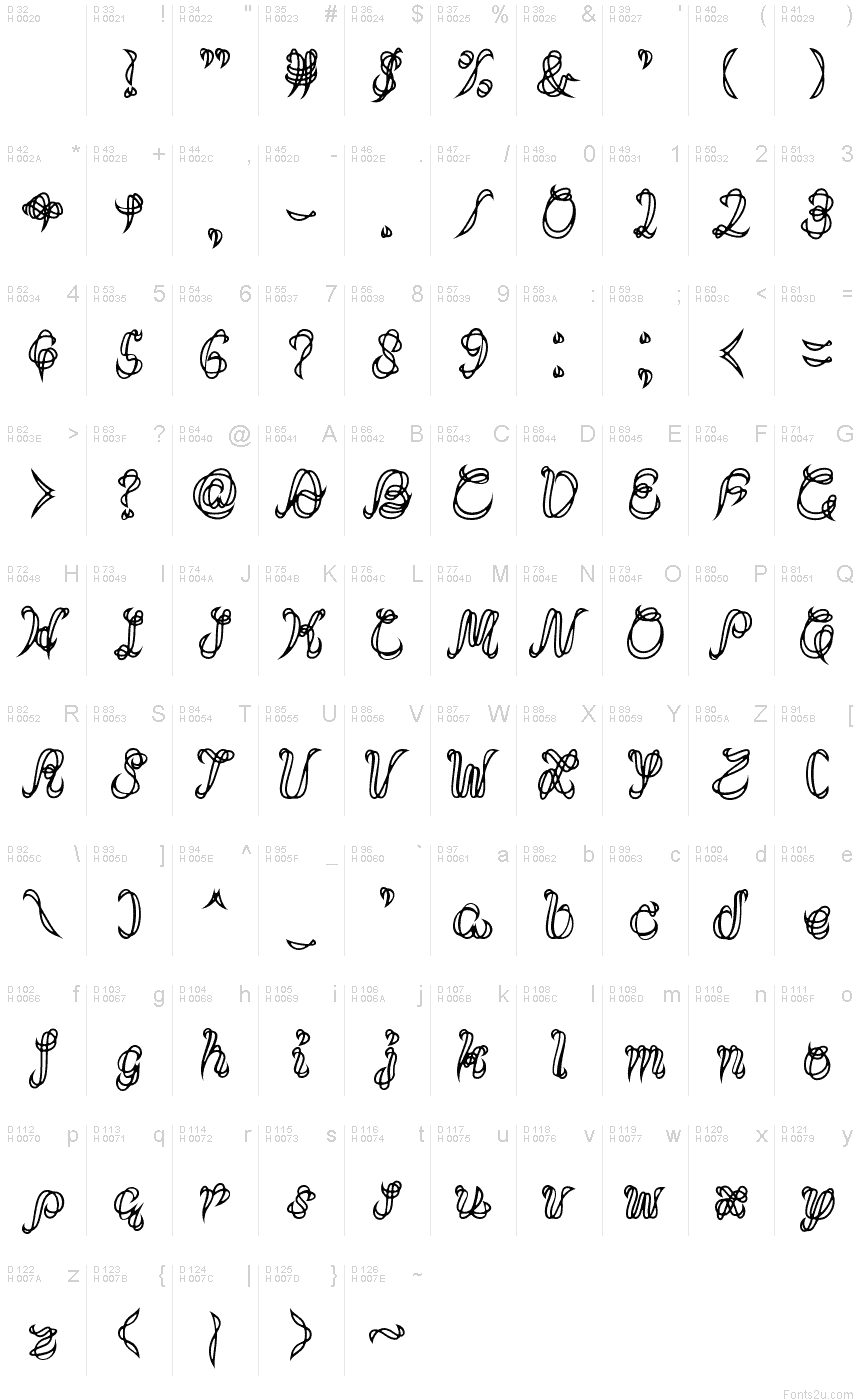
Goutte Alphabet od Kivart to darmowy, botaniczny krój pisma odręcznego w klimacie Art Nouveau. Litery wiją się w długie, przypominające pnącza pociągnięcia i zamknięte pętle, które kojarzą się ze łodygami, pąkami i płatkami kwiatów. Nadaje to krojowi lekko ornamentalny rytm, znacznie odbiegający od swobodnych krojów typu marker.
Sprawdzi się na opakowaniach perfum, w logotypach butików, na okładkach książek, w menu kawiarni czy na plakatach, gdzie motyw roślinny może zdefiniować całość projektu. Jako darmowy font, doskonale nadaje się również do krótkich haseł reklamowych, monogramów i inicjałów, ponieważ każda litera zachowuje się jak mały rysunkowy ornament, a nie jak neutralny, odręczny znak.